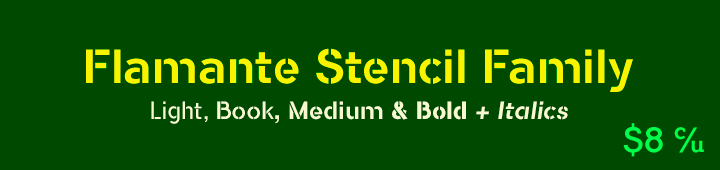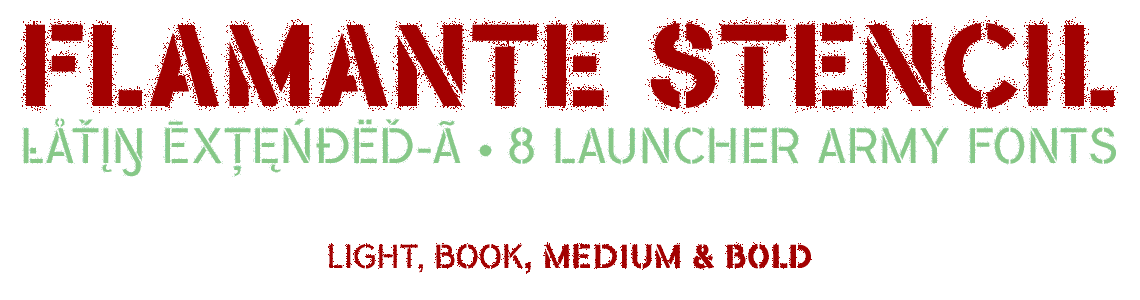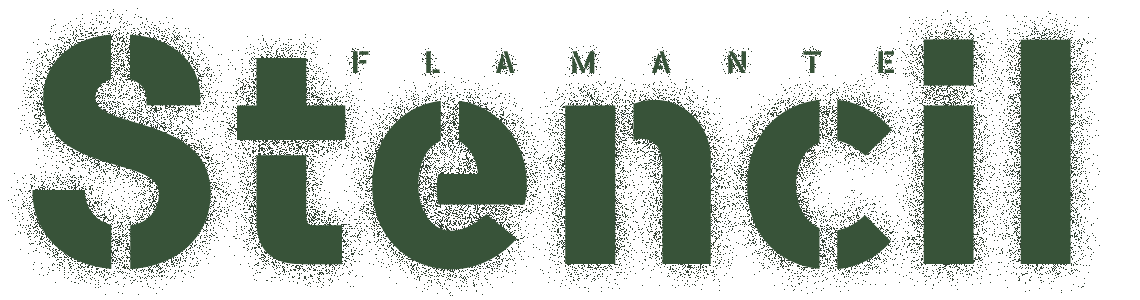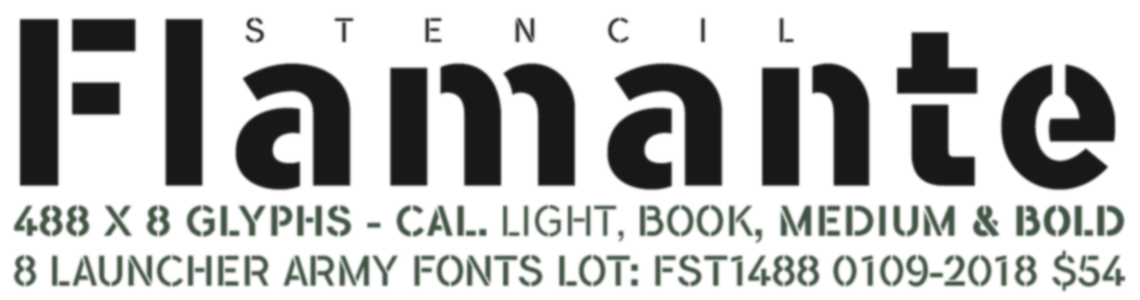
Flamante Stencil fonts
Flamante Stencil, familia de fuentes militares: Light, Book, Medium & Bold
Flamante Stencil Family Fonts
Flamante Stencil Typeface Family
Flamante Stencil - Army Fonts Latin Extended-A
Stencil Family Fonts
Estilo: Stencil, Geométrica, Sans Serif, Militar
Proporción: Light, Book, Medium, Bold, Italic
Light, Book, Medium & Bold + Italics